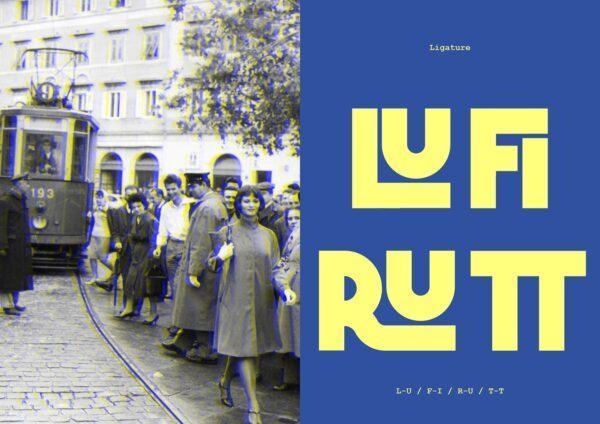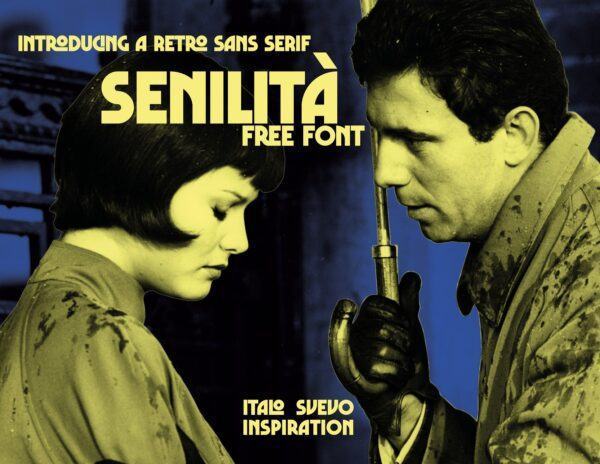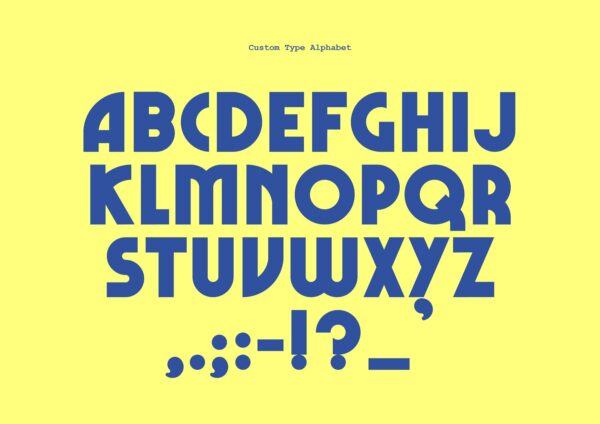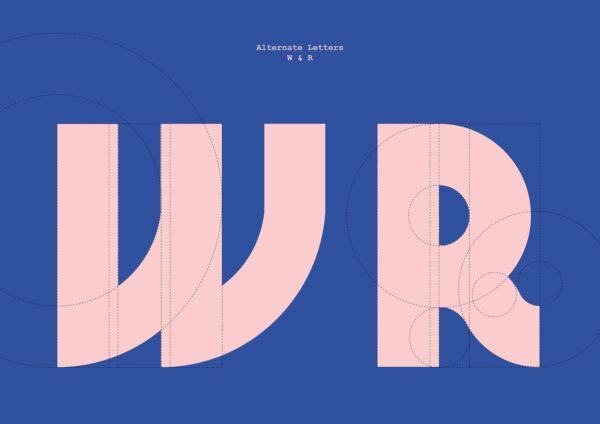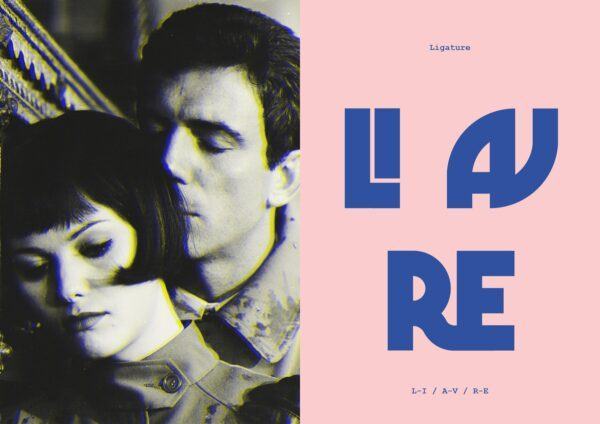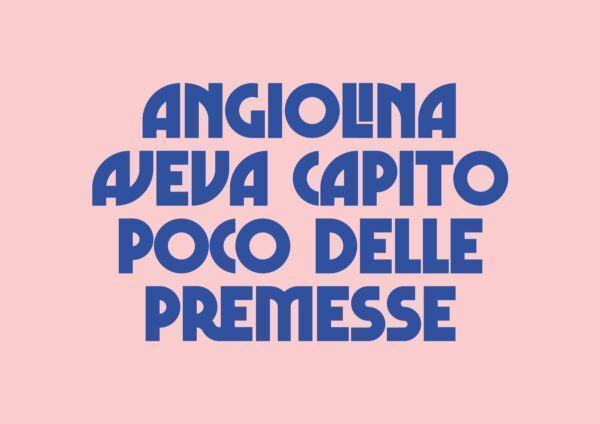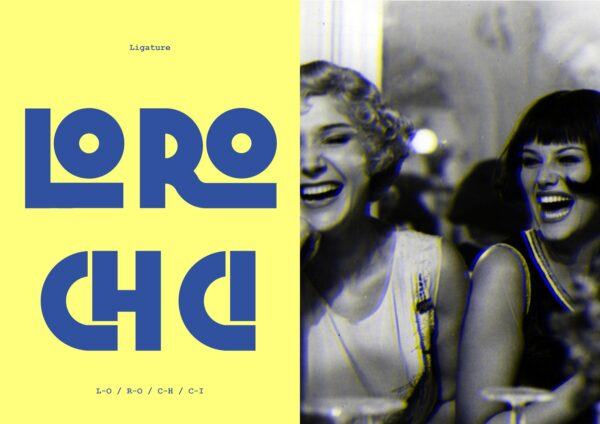
Senilità – Free Retro Display Font
Senilità là một phông chữ hiển thị retro miễn phí được tạo ra bởi  Pietro Filippeschi. Phông này có kiểu dáng lấy cảm hứng từ các bộ phim cổ điển của Ý, chủ đề trang trí nghệ thuật và giữa thế kỷ.
Bạn sẽ tìm thấy nhiều chữ ghép tùy chỉnh sẽ giúp bạn tạo các thiết kế kiểu hấp dẫn với phông chữ viết hoa này.